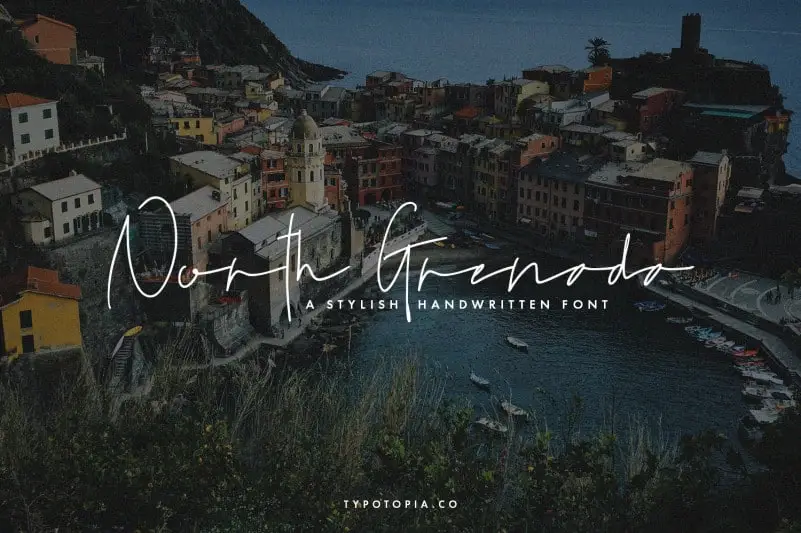
North Grenada Handwritten Font – Fonte Grátis
North Grenada Handwritten Font
A North Grenada Handwritten Font é uma opção para designers que buscam adicionar um toque elegante e único a seus trabalhos. Esta fonte vem com seis variações refinadas, cada uma cuidadosamente criada para tornar os designs mais atrativos e sofisticados. Ela apresenta letras delicadamente escritas em estilo minúsculo, ideal para criar textos chamativos que se destacam de forma elegante. Seja para criação de flyers, design gráfico ou qualquer projeto envolto em texto, a North Grenada Handwritten Font oferece uma solução de fonte perfeita. Ela é um recurso útil e encantador para quem busca adicionar personalidade aos projetos digitais com apenas um clique.